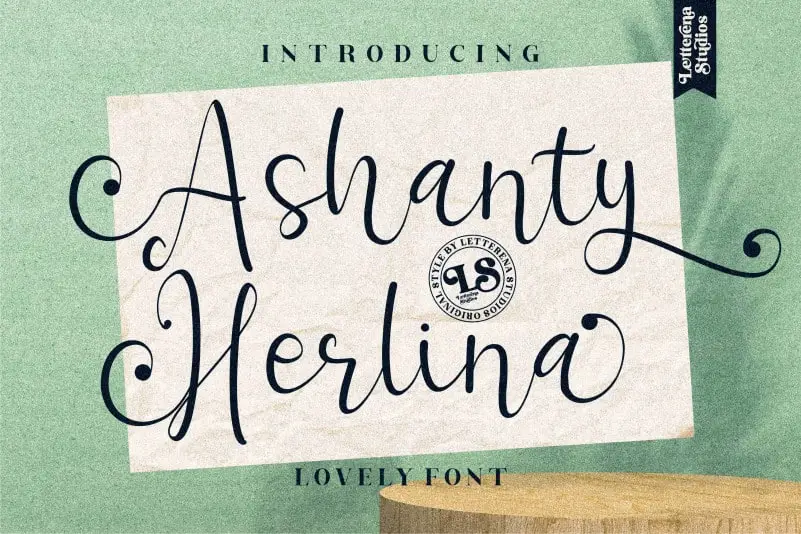
A Ashanty Herlina Script Font é uma deliciosa tipografia script que encanta a primeira olhada com sua delicadeza e personalidade peculiar. Seja para frases criativas ou letras de marca inovadoras, essa fonte traz vida a qualquer idea mais inspiradora. Ela é ideal para quem busca um toque único e charmoso em seus projetos gráficos. Composta por detalhes encantadores e uma escrita fluida, Ashanty Herlina Script Font é perfeita para dar aquele toque especial às suas criações de design. Seja você um designer gráfico, ilustrador ou artista digital, essa fonte trará alegria aos seus projetos com sua rica herança de letras e estilo único.